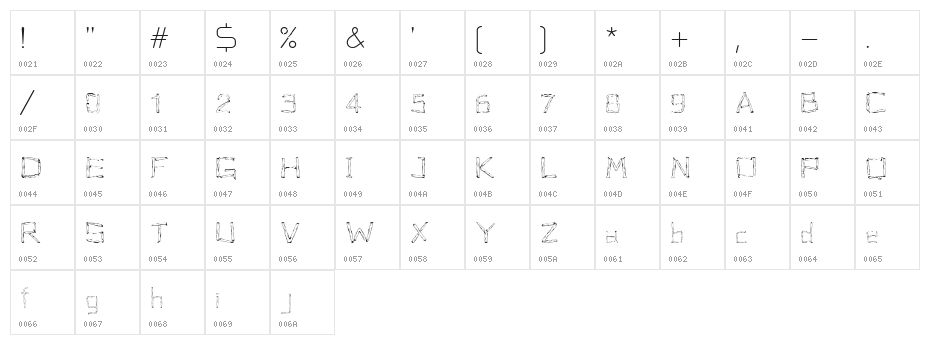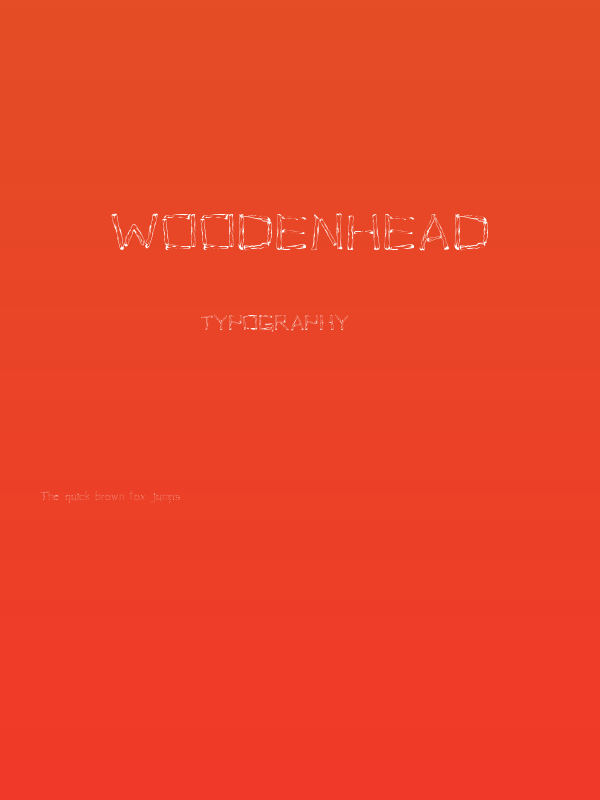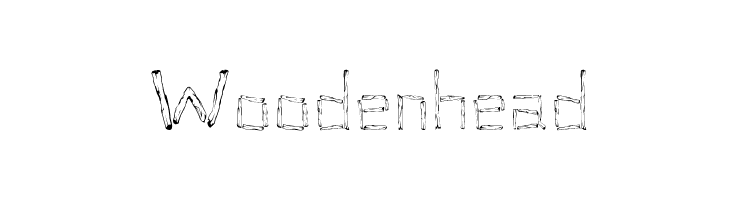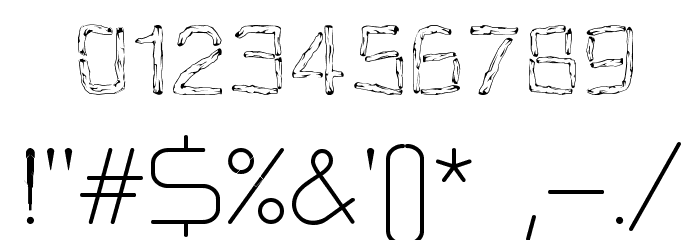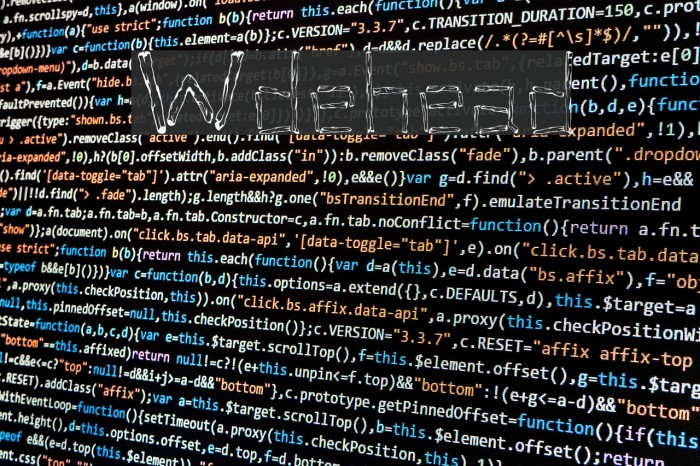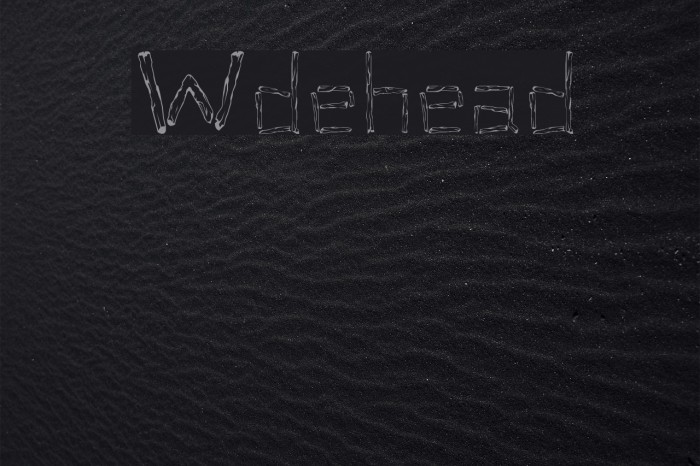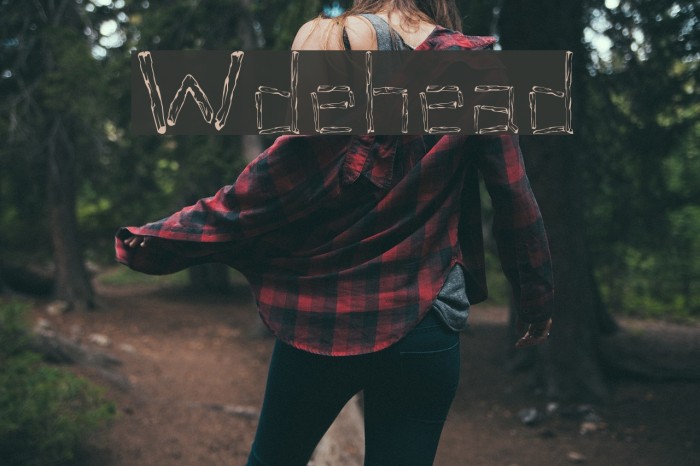
Woodenhead Font
| Style général | Rustic, Natural, Handcrafted |
| Projets proposés | Ideal for eco-friendly branding, nature-themed posters, rustic wedding invitations, and artisanal product packaging. |